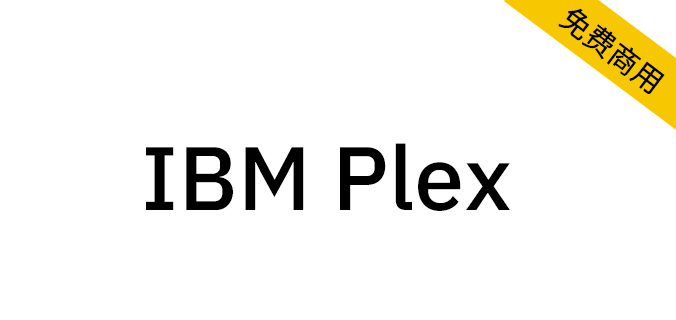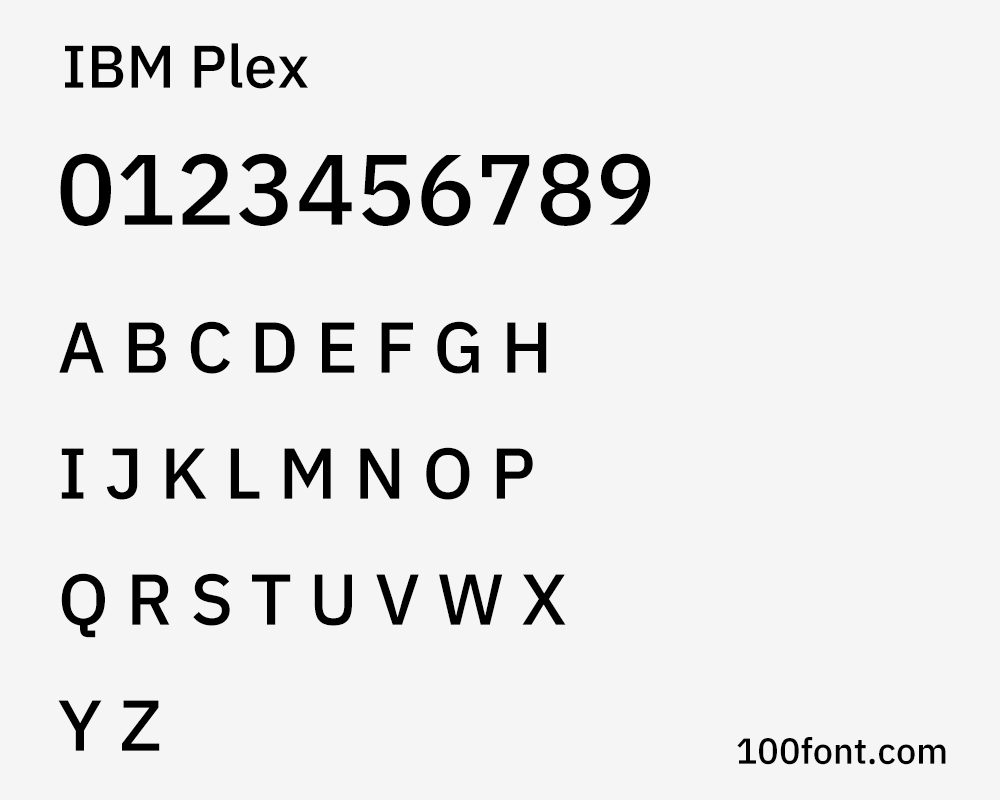
认识我们新的企业字体系列 IBM Plex® 字体。它是全球性的,它是通用的,而且它显然是 IBM。
Meet the IBM Plex® typeface, our new corporate typeface family. It’s global, it’s versatile and it’s distinctly IBM.
我们精心设计了 IBM Plex 字体,既能满足我们作为一家全球科技公司的需求,又能表达我们作为 IBM 人的身份。我们花了两年的时间和大量的工作才来到这里,但今天我们有一个标志性的字体,我们很自豪也很高兴能与世界分享。
We designed the IBM Plex typeface carefully to both meet our needs as a global tech company and express who we are as IBMers. It took two years and a lot of work to get here, but today we have a signature typeface we’re proud and excited to share with the world.
IBM Plex 字体是一个开源项目,可按照 Open Font License (OFL) 下载和使用。IBM Plex 系列有 Sans、Serif、Mono 和 Sans Condensed,全部带有罗马和真正的斜体。这些字体被设计为在用户界面 (UI) 环境以及其他媒体中运行良好。该项目提供所有源文件和文件格式以支持大多数印刷情况。目前,IBM Plex Sans 支持扩展拉丁文、阿拉伯文、西里尔文、梵文、希腊文、希伯来文、日文、韩文和泰文。中文将在2022年跟进。
The IBM Plex typeface is an open-source project and available for download and use following the Open Font License (OFL). The IBM Plex family comes in Sans, Serif, Mono and Sans Condensed, all with roman and true italics. The fonts have been designed to work well in user interface (UI) environments, as well as other mediums. This project provides all source files and file formats to support most typographical situations. Currently, IBM Plex Sans supports Extended Latin, Arabic, Cyrillic, Devanagari, Greek, Hebrew, Japanese, Korean and Thai. Chinese will follow in 2022.
IBM Plex Family 有三大字体类型:Sans-serif(无衬线体)、Serif(衬线体)和 Mono(等宽字体),每种类别有八种不同字重:Thin、ExtraLight、Light、Text、Regular、Medium、Bold、SemiBold,也有为斜体设计的 Italic 系列。